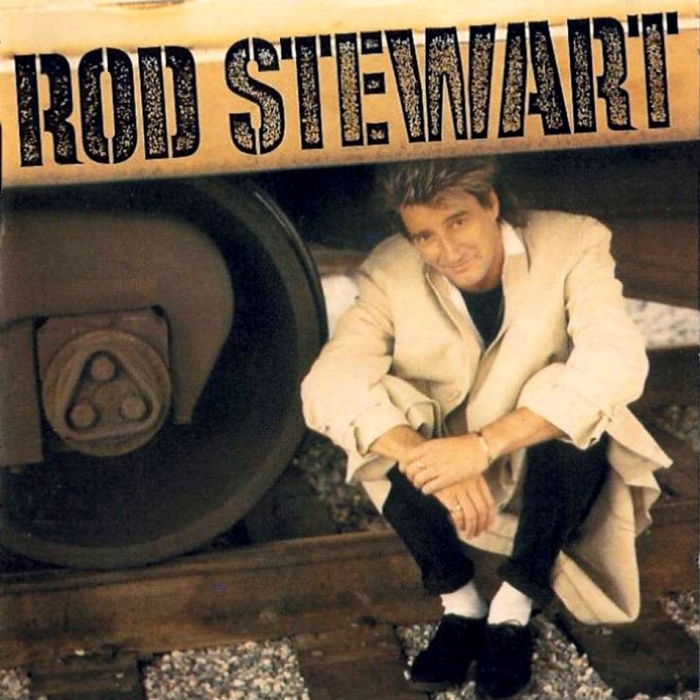
Rod-Stewart-Album
Kann mir jemand sagen wie diese Schrift heißt oder ob es eine ähnliche gibt?
das album ist ja von mitte der 80er, also ist die schrift wohl keine ursprünglich digitale.
mich erinnert sie an diese hier:
die einschnitte sind schmaler, aber vielleicht ist diese version auf der basis einer anderen optischen größe digitalisiert worden (oder die einschnitte wurden für den schriftzug vergrößert).
Mir ist es um den Schabloneneffekt gegangen.
Die Filmotype Quiet passt wirklich sehr gut! Vielen Dank.